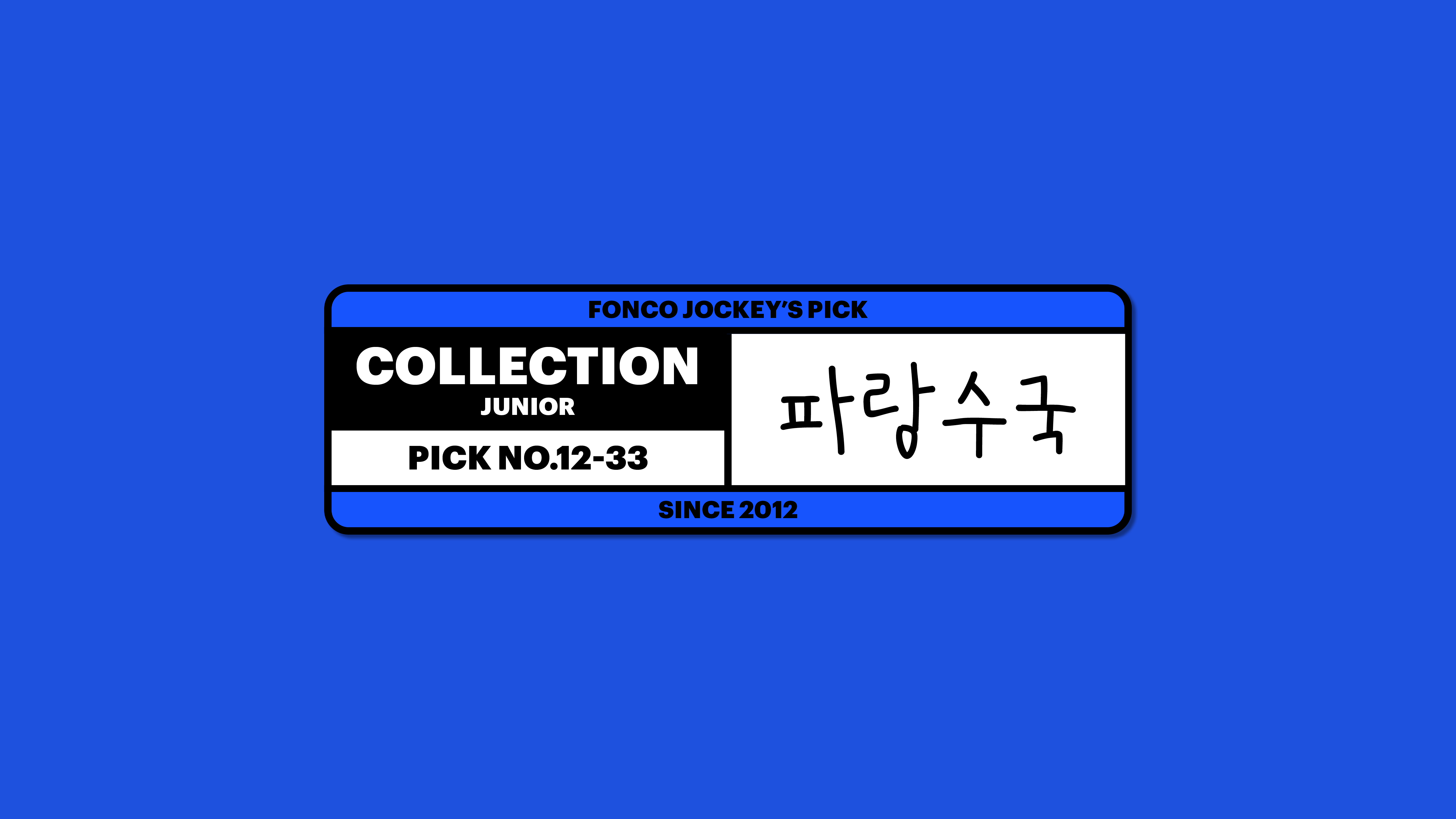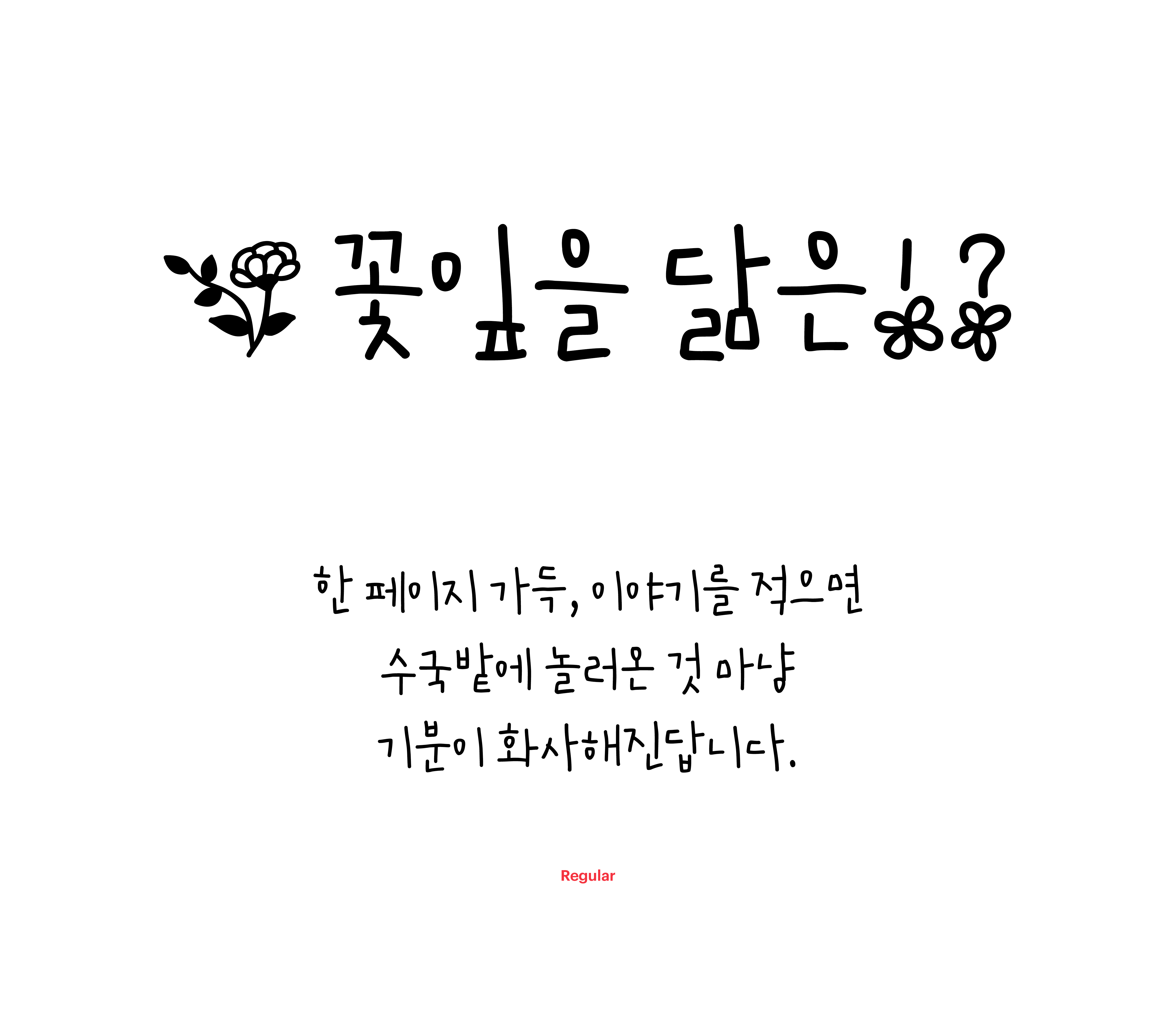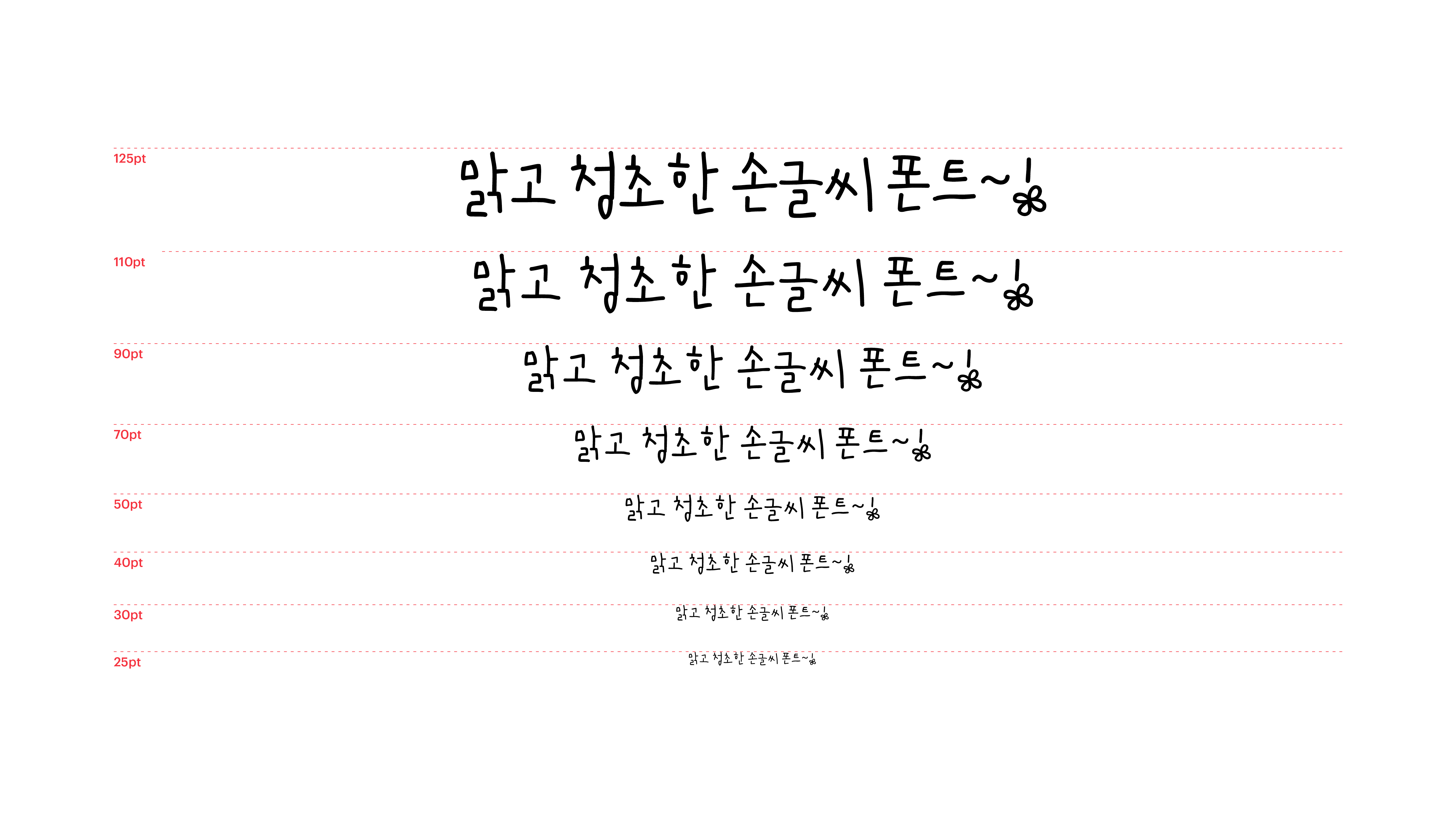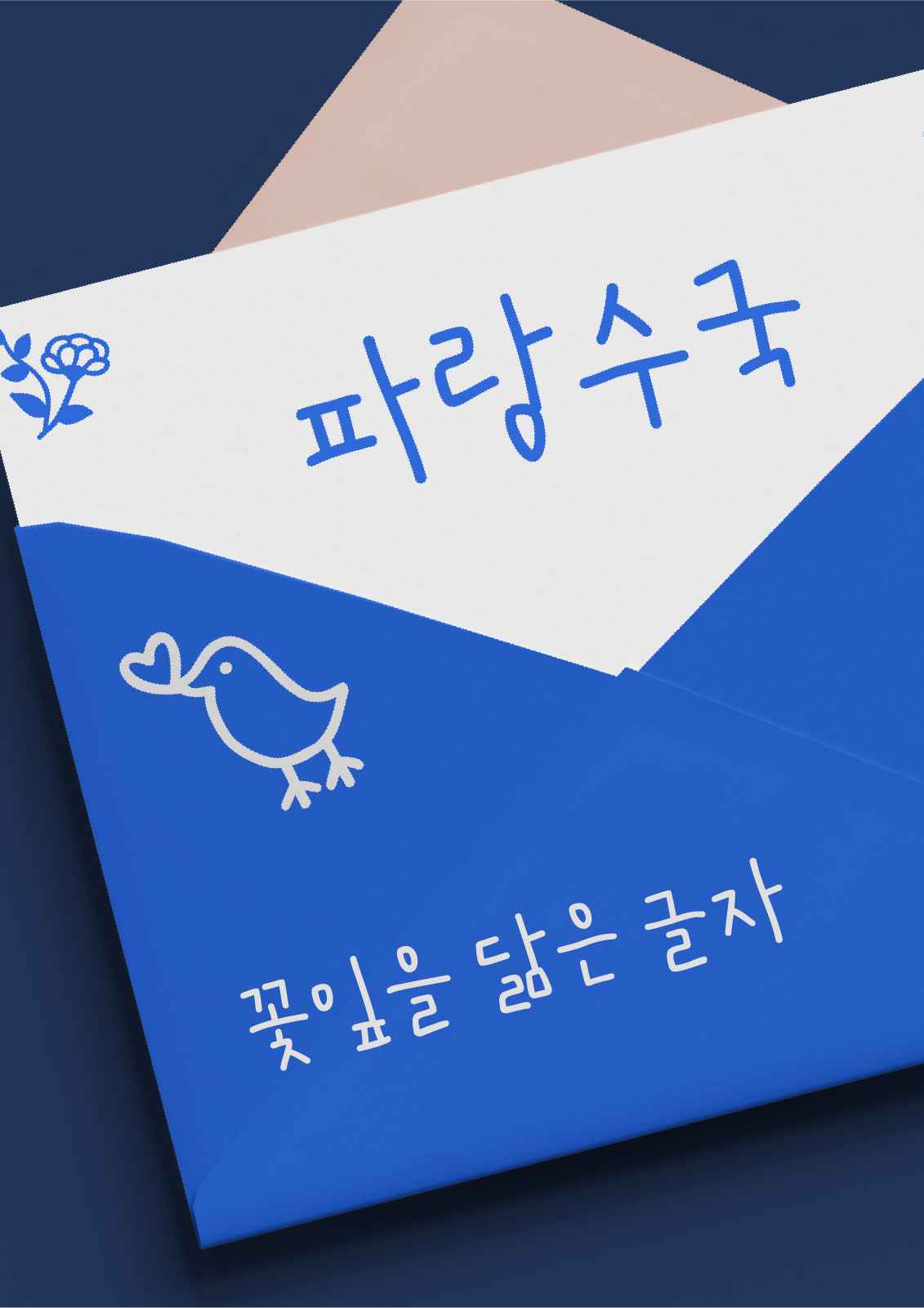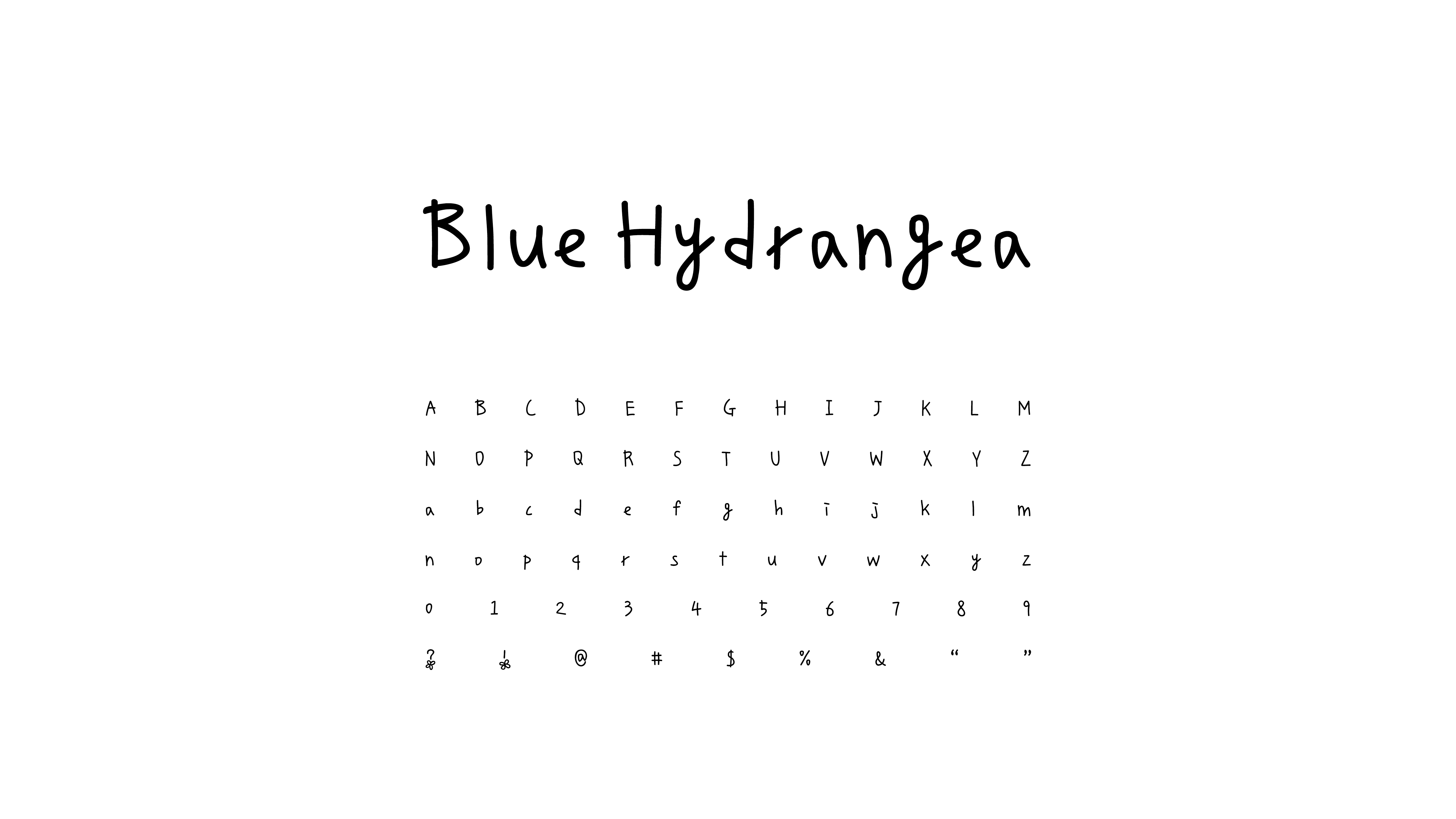
파랑수국
Yoon 파랑수국
길게 뻗은 중성에 꽃잎을 닮은 조그만 초성이 수수하게 매치되어 있는 폰트입니다. 한 페이지 가득, 이야기를 적으면 수국밭에 놀러온 것 마냥 기분이 화사해진답니다. 맑고 청초한 이 손글씨 폰트가 모니터 가득 투명한 이슬들을 불러올 것만 같아요.